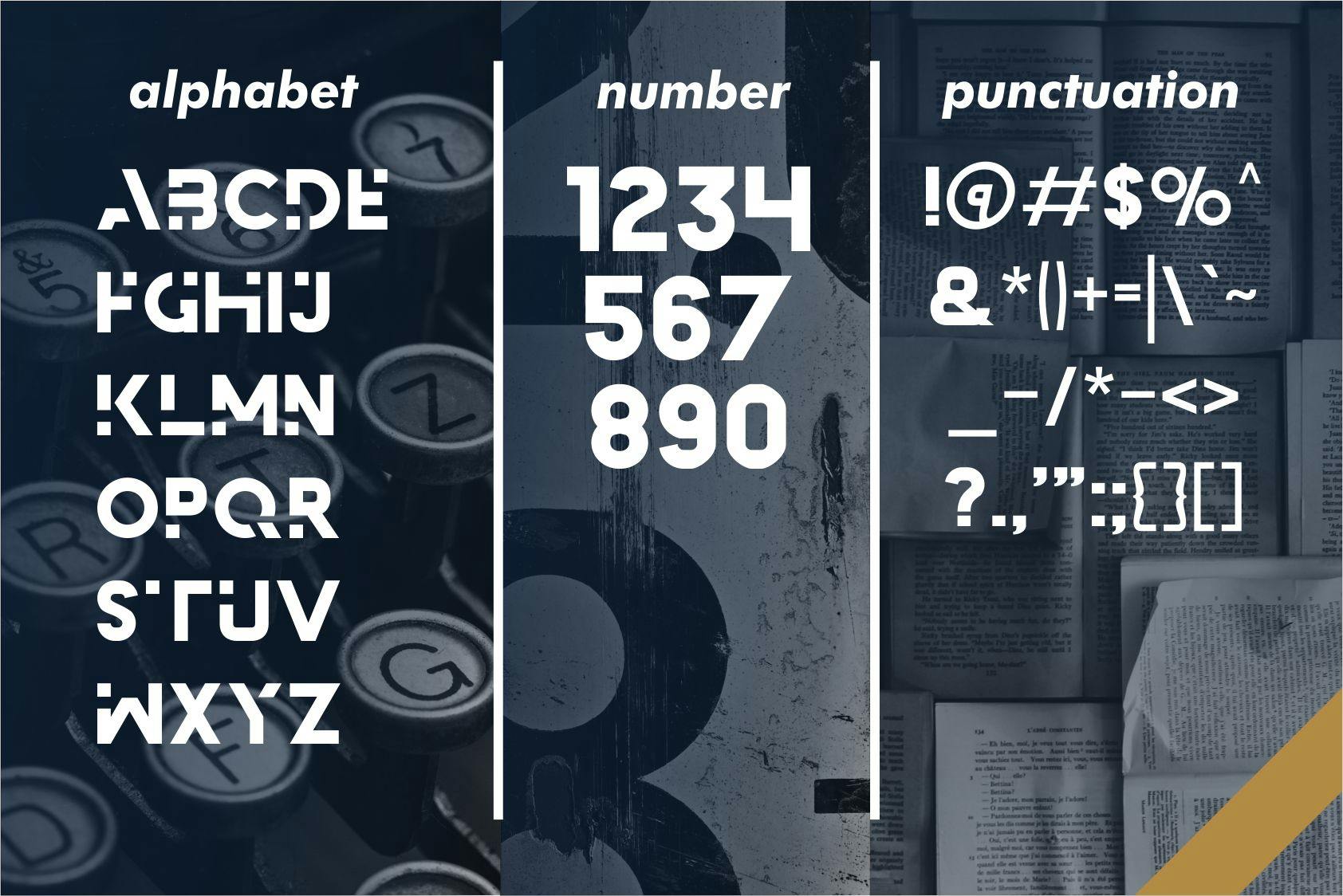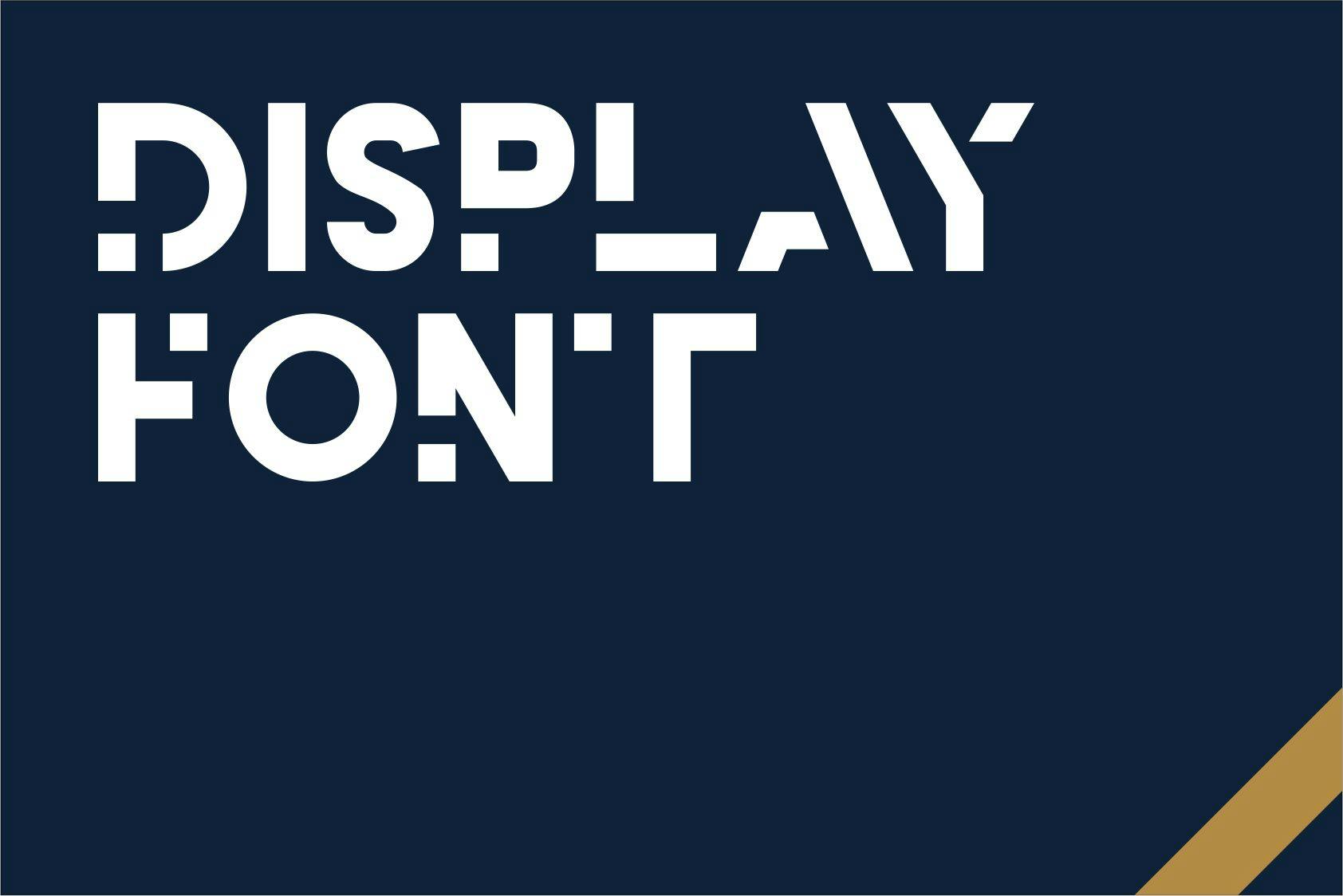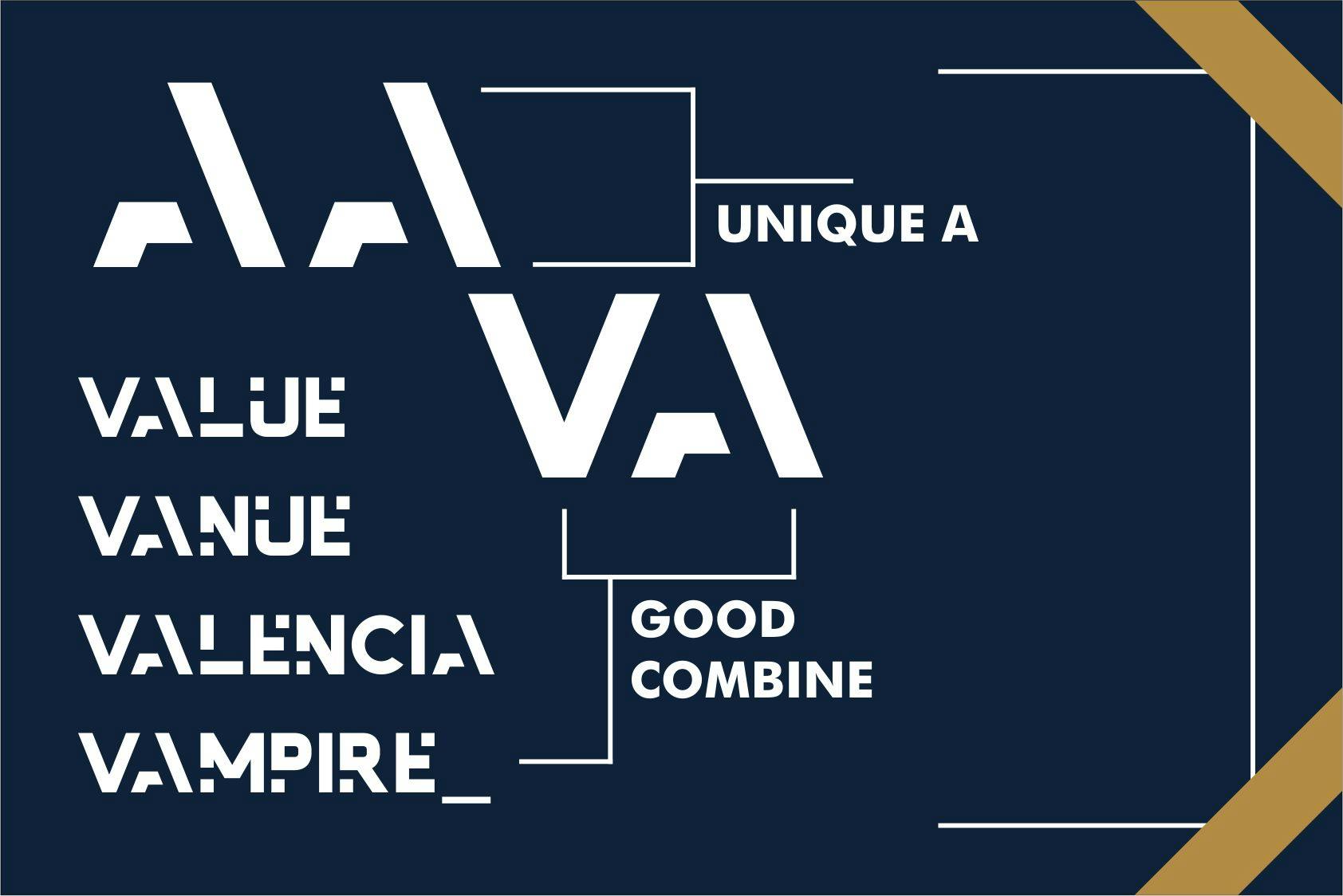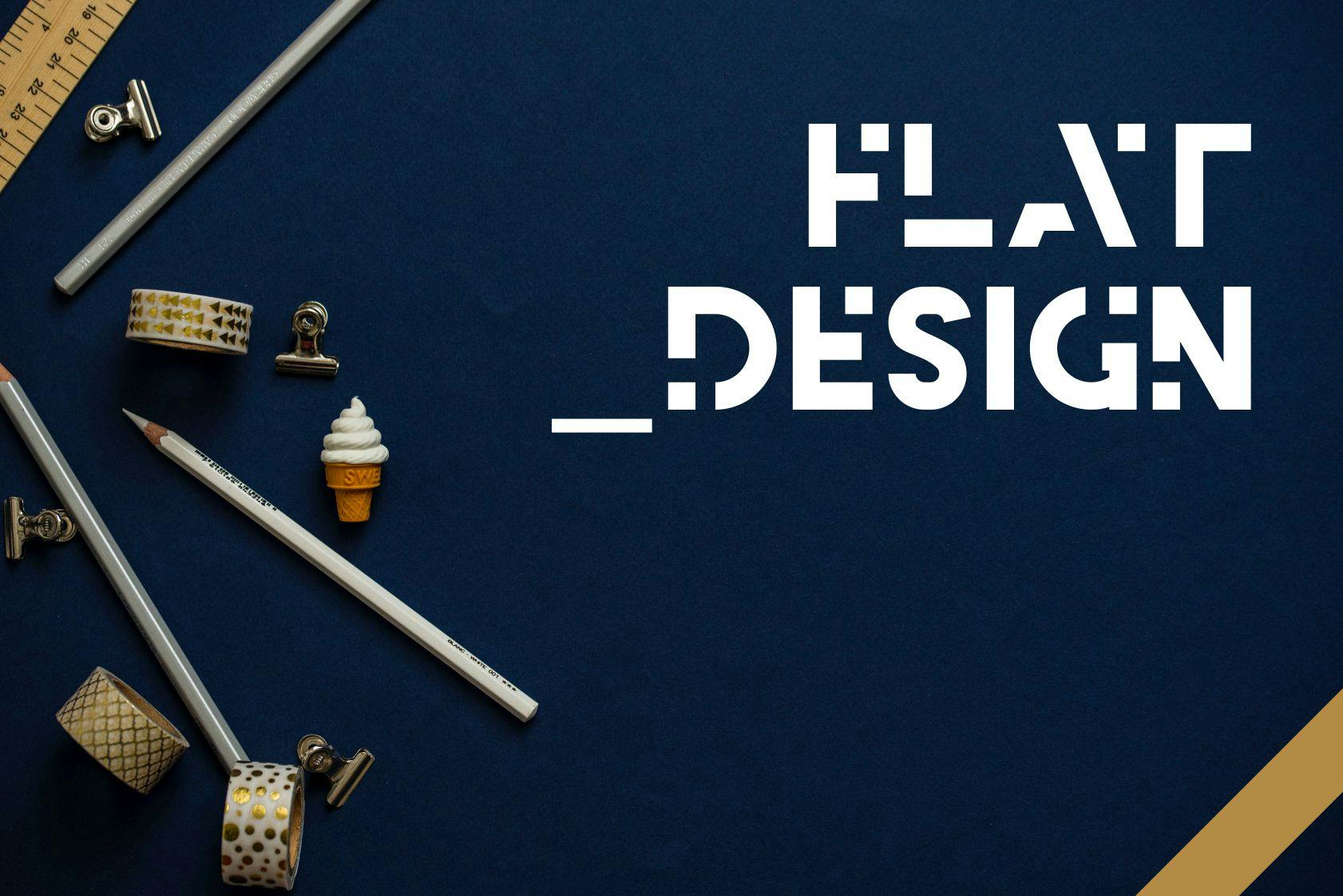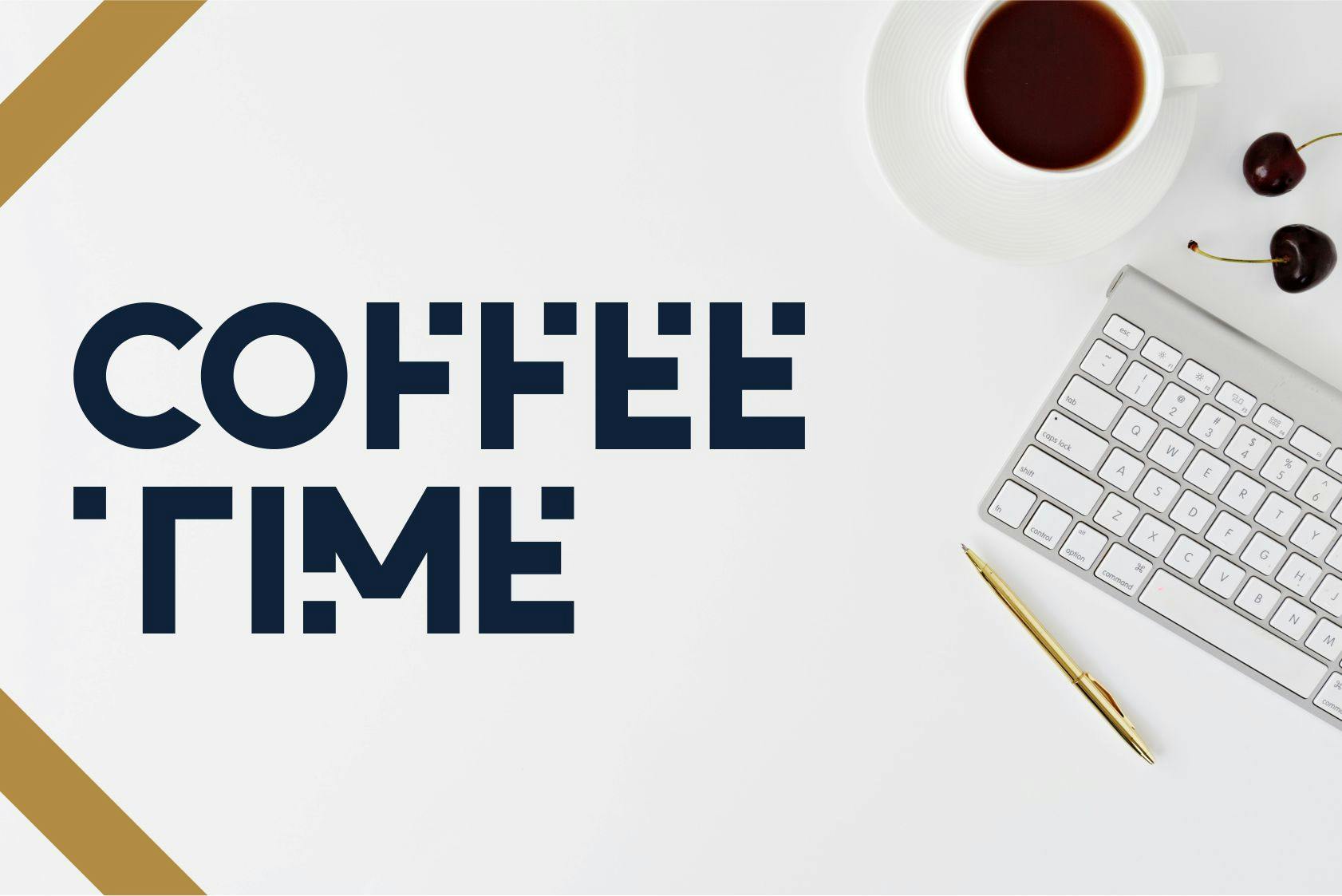
فونت هاوکس شامل حروف بزرگ، اعداد و مجموعهای از نشانهگذاریهای متنوع است. این فونت بدون سر (sans serif) با سبک مدرن طراحی شده و برای پوسترها، طراحی وب، برندینگ، تصاویر، نشانها و برخی دیگر از پروژهها مناسب است.